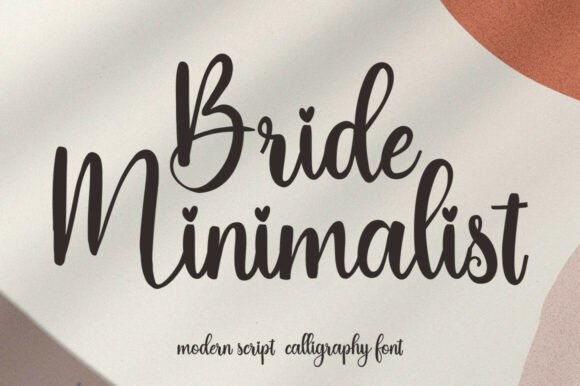
Bride Minimalist Font
Mencari elemen desain yang tepat bisa jadi sulit, namun Bride Minimalist Font menawarkan koleksi luar biasa yang akan langsung meningkatkan kualitas karya Anda.
Baik Anda membuat produk POD (Print on Demand), undangan pernikahan, atau grafis media sosial, Bride Minimalist Font adalah pilihan yang sangat ideal.
Tips Ahli: Padukan elemen-elemen ini dengan font pendamping untuk menciptakan desain unik dan menarik yang menonjol di pasaran.